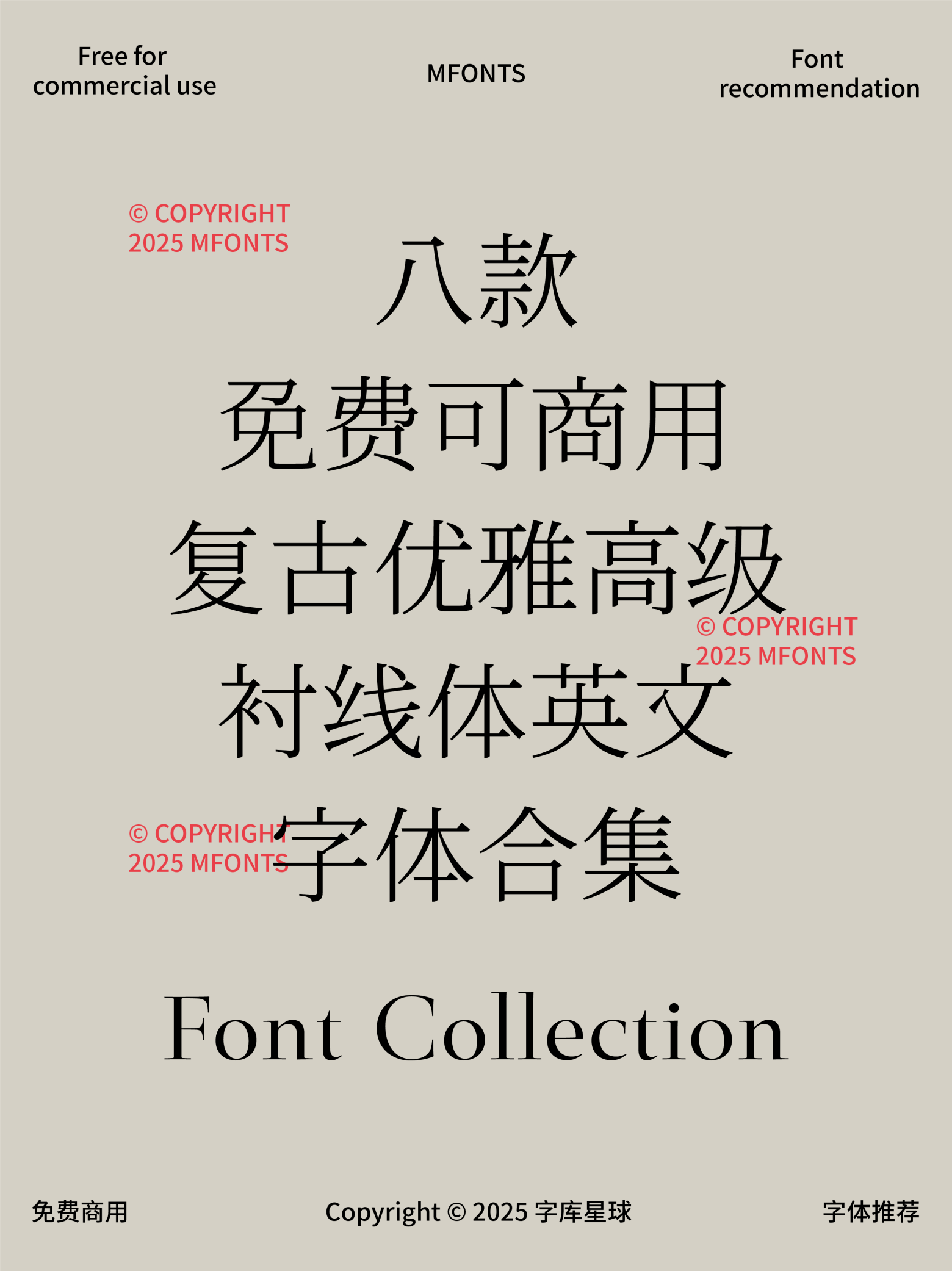
八款免费可商用复古优雅高级衬线体英文字体合集
今天分享八款免费可商用复古衬线英文字体安利给你们!每一款都自带优雅高级感,海报、包装、品牌设计直接开挂,快码住这份提升审美的神器
经典永不过时的衬线字体,笔画粗细对比鲜明,细节处藏着精致的小韵味。用在品牌 LOGO 或标题设计里,瞬间透出贵气感,简直是复古风设计师的心头好!
英文衬线字体界的 “老钱风” 代表,笔触沉稳大气,排版时自带庄重感。无论是书籍封面还是高端品牌宣传,都能让文字散发出历经岁月的高级质感。